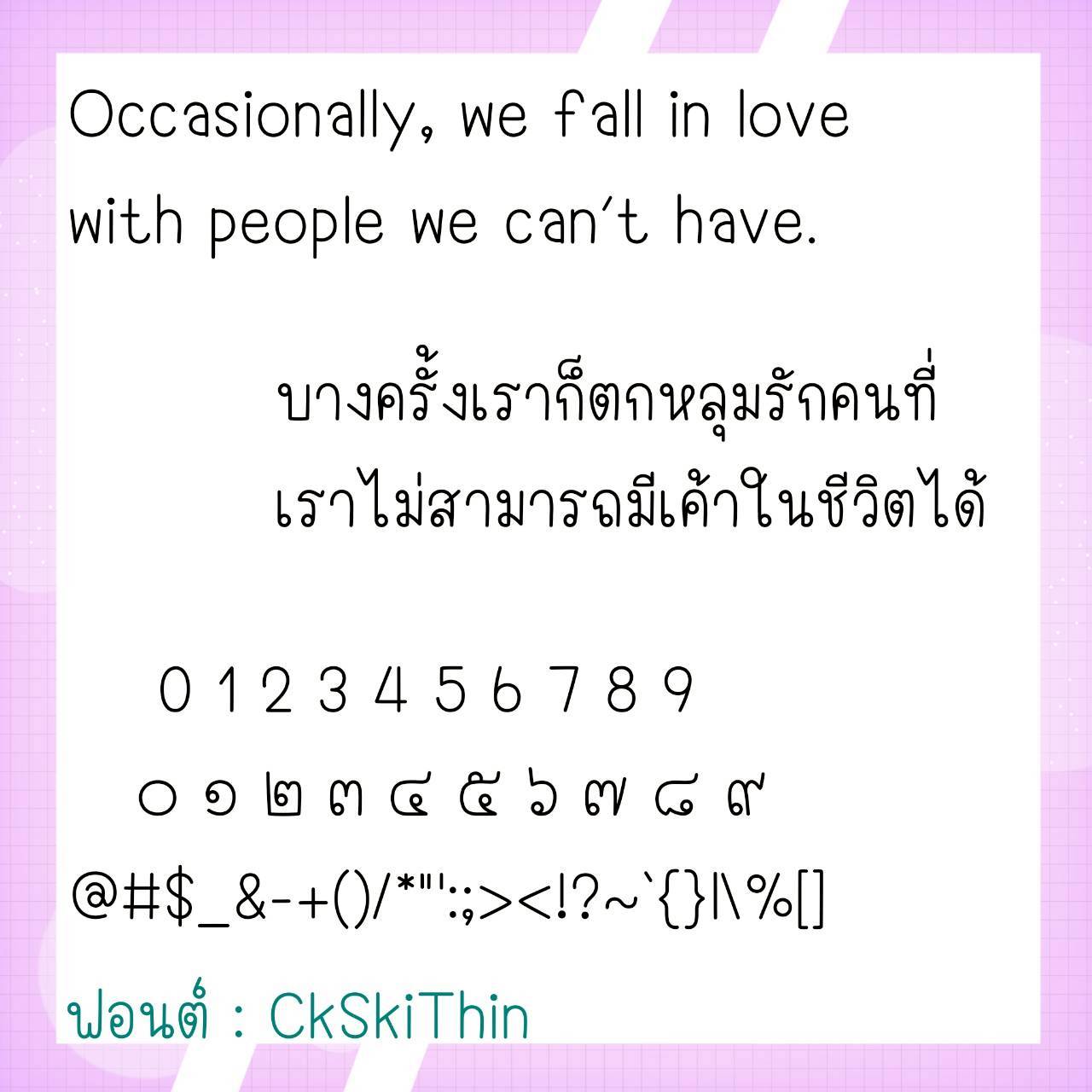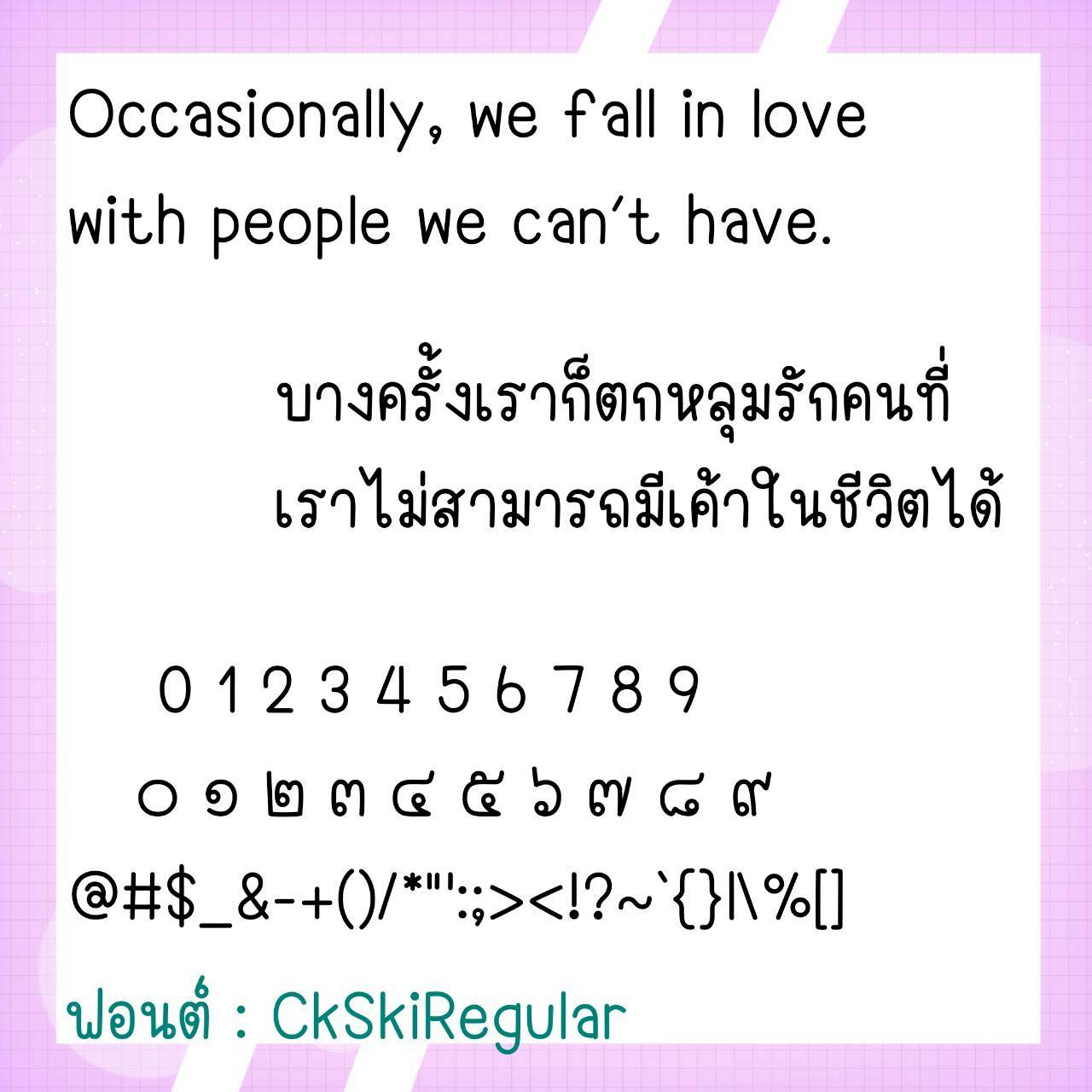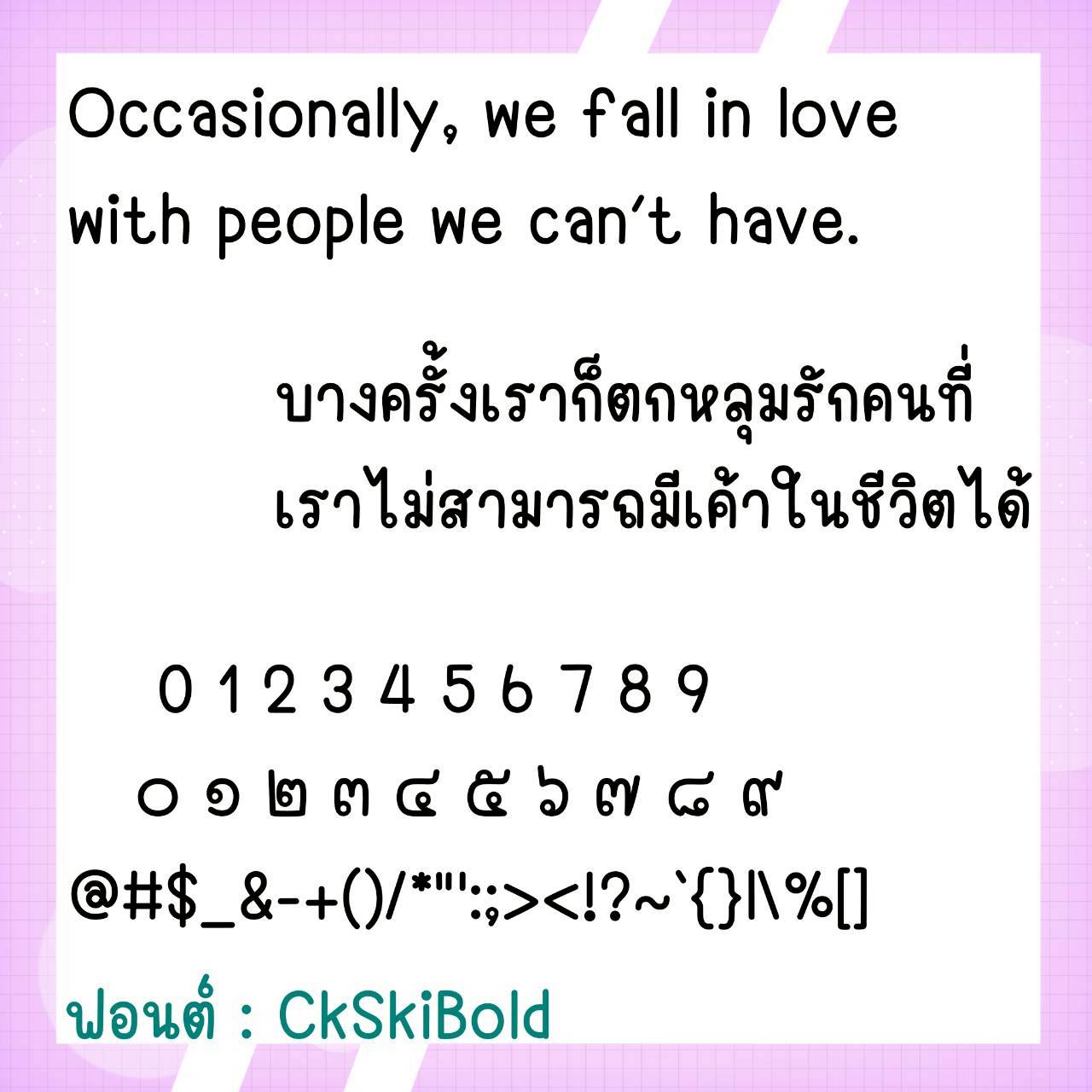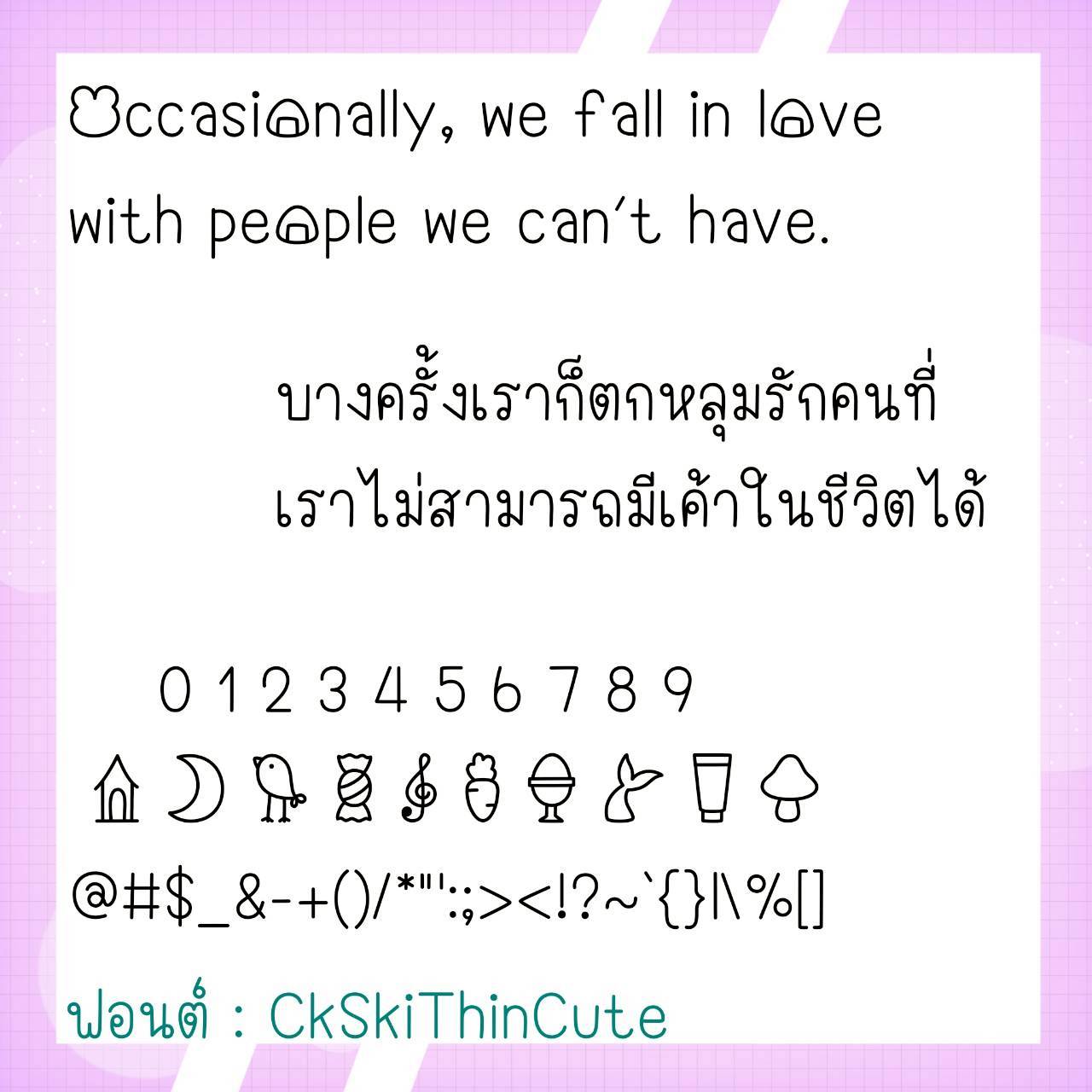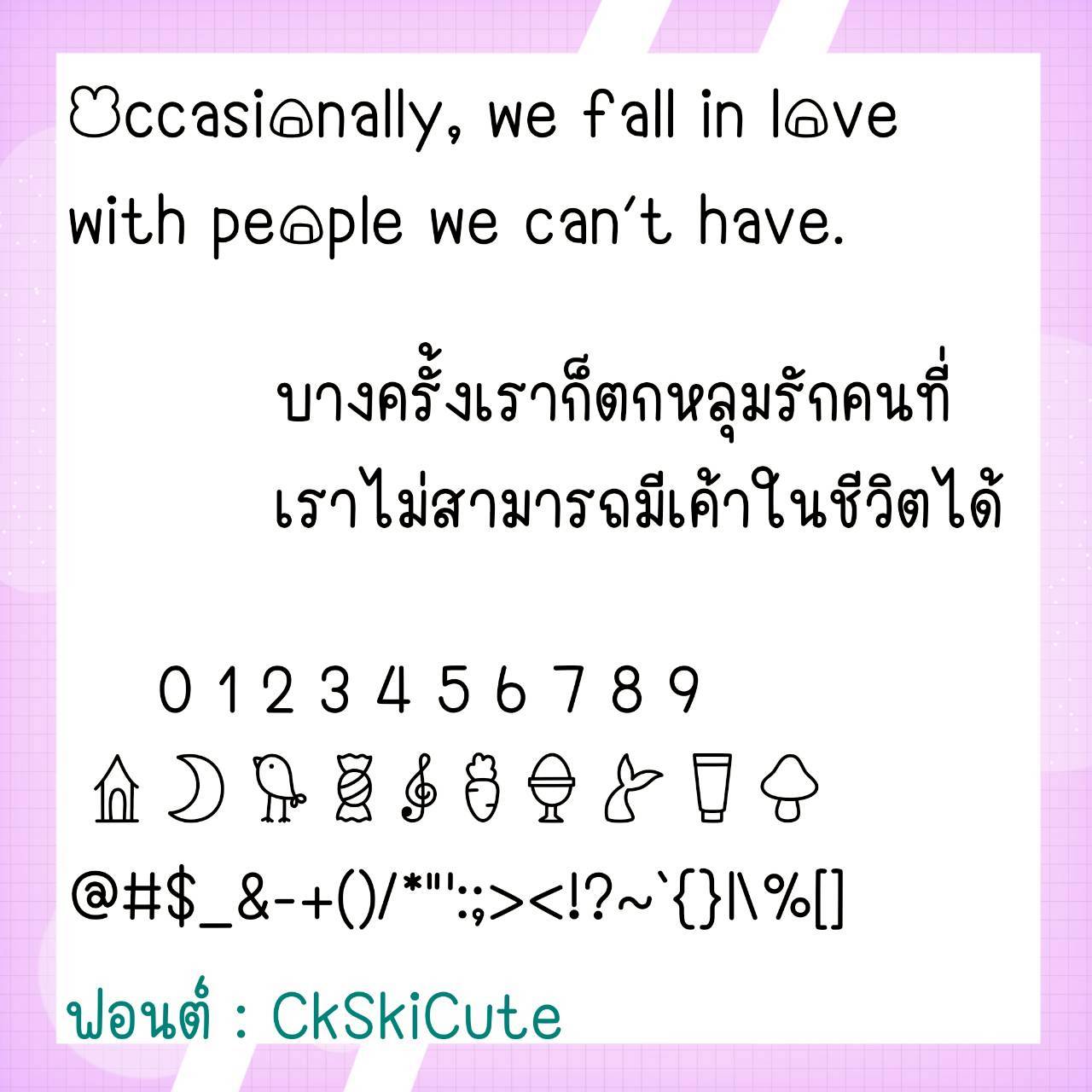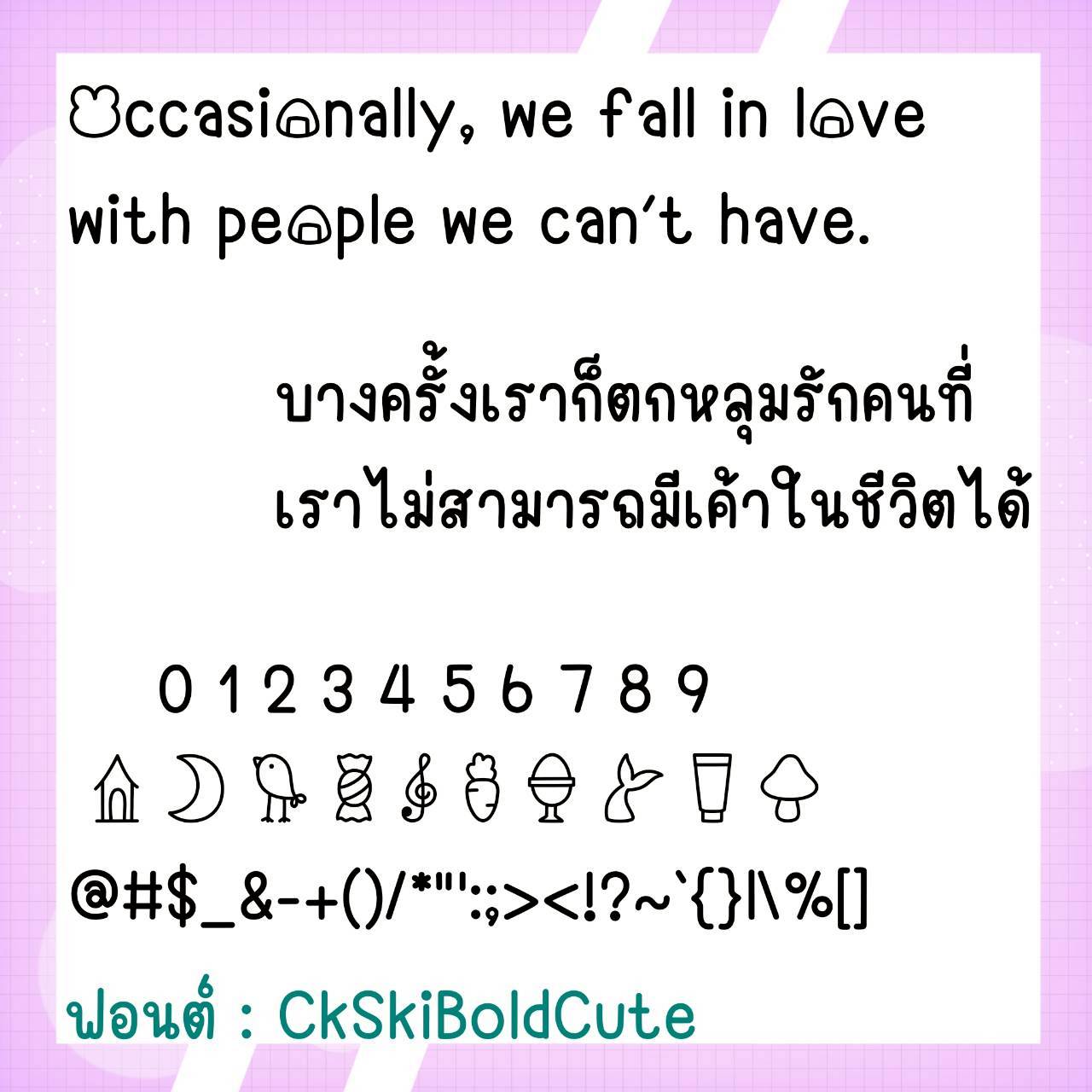
Font CkSki
🔸 ฟอนต์ลายมือแนวน่ารักๆ ตัวออกผอมๆ ดูไม่น่าเบื่อ มีความวัยรุ่นในตัว แต่ยังอ่านง่าย และยังมีไฟล์อิโมจิน่ารักๆที่ใช้แทนเลขไทยให้ด้วยค่ะ 🥰💙
🔹 A cute, handwritten font with slim characters that’s not boring and has a youthful feel, yet is still easy to read. It also includes cute emoji files that can be used to replace Thai numerals. 🥰💙
🔸ฟอนต์ลายมือแนววัยรุ่น มีความยึกยัก น่ารักมีสไตล์ดูมีลูกเล่น ดูไม่น่าเบื่อ และยังมีไฟล์อิโมจิน่ารักๆที่ใช้แทนเลขไทยให้ด้วยค่ะฟอนต์ปรับสระเรียบร้อยไม่ลอย ไม่เหลี่ยม ใช้งานได้กับทุกโปรแกรม ได้ทั้ง ios(รองรับกับแอพต่างๆที่รองรับฟอนต์ในios เช่น Goodnote, Procreate)/android/คอมฯ/Ps/Word,Excel ได้หมดจ้าาาาา❤️❤️❤️